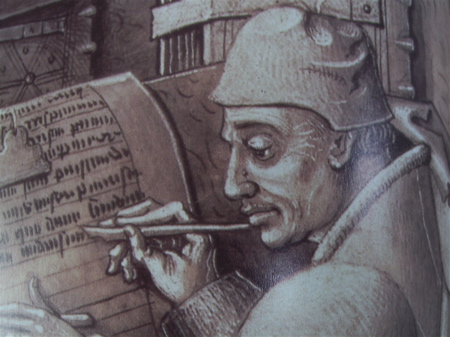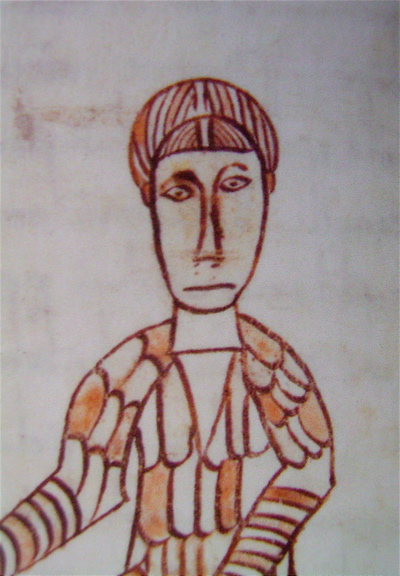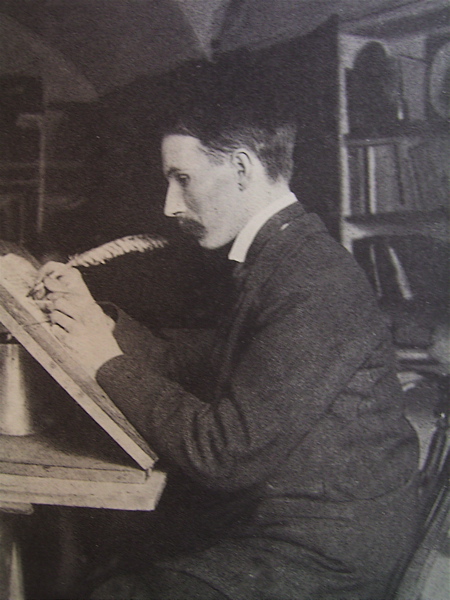
カリグラファーの顔
このお方、カリグラフィーや活字を学んでいる方なら多分誰でもご存知のエドワードジョンストンです。
羽ペンを持って姿勢よく傾斜板で書いていますね。左手にはちゃんとペンナイフかなにかを持って、紙を押さえながら書いています。
こんなにきちんとした格好で書いていたのかしらん??
ネクタイしたスーツ姿ですよ!
昔のカリグラファーの姿は余り残されていませんが、有名なのは15世紀のジャンミエロさん。
彼の姿を書いた絵は2点だけ残っているそうですよ。
詳しくは高宮利行先生著の「本と人の歴史事典」に詳しく載っています。
ジョンストンさんは写真だから間違いはないでしょうが、肖像となるとまったく違う人だったということもありえるのかもしれません。
さて、肖像と言ったら、やっぱり好きなのはコレ!
以前mojitor-hさんやmojitor-tさんとスイスのサンクトガレン修道院の図書館に写本を見に行ったときに、ちょうどアルクィンの没1200年の記念シンポジウムのよう学会が開かれていました。そのパンフに載っていたアルちゃんの顔。
味がある良い顔してますよね。賢そう。
アルクィンはイギリスのヨーク出身の修道士でしたが,フランク王国のカール大帝(シャルルマーニュ)が招いてフランスのトゥールで、学者として活躍したのです。
カロリングルネッサンスにおける文化運動では重要な役割を果たし、あのカロリンジャンの書体を生み出したと言われています。彼が実際に書いたかどうかはわからない、と以前取った歴史のクラスでは教わりましたが、実際はどうだったんでしょうねぇ。